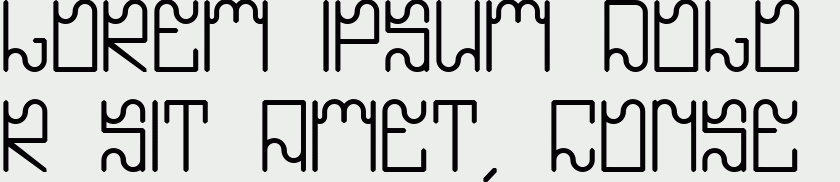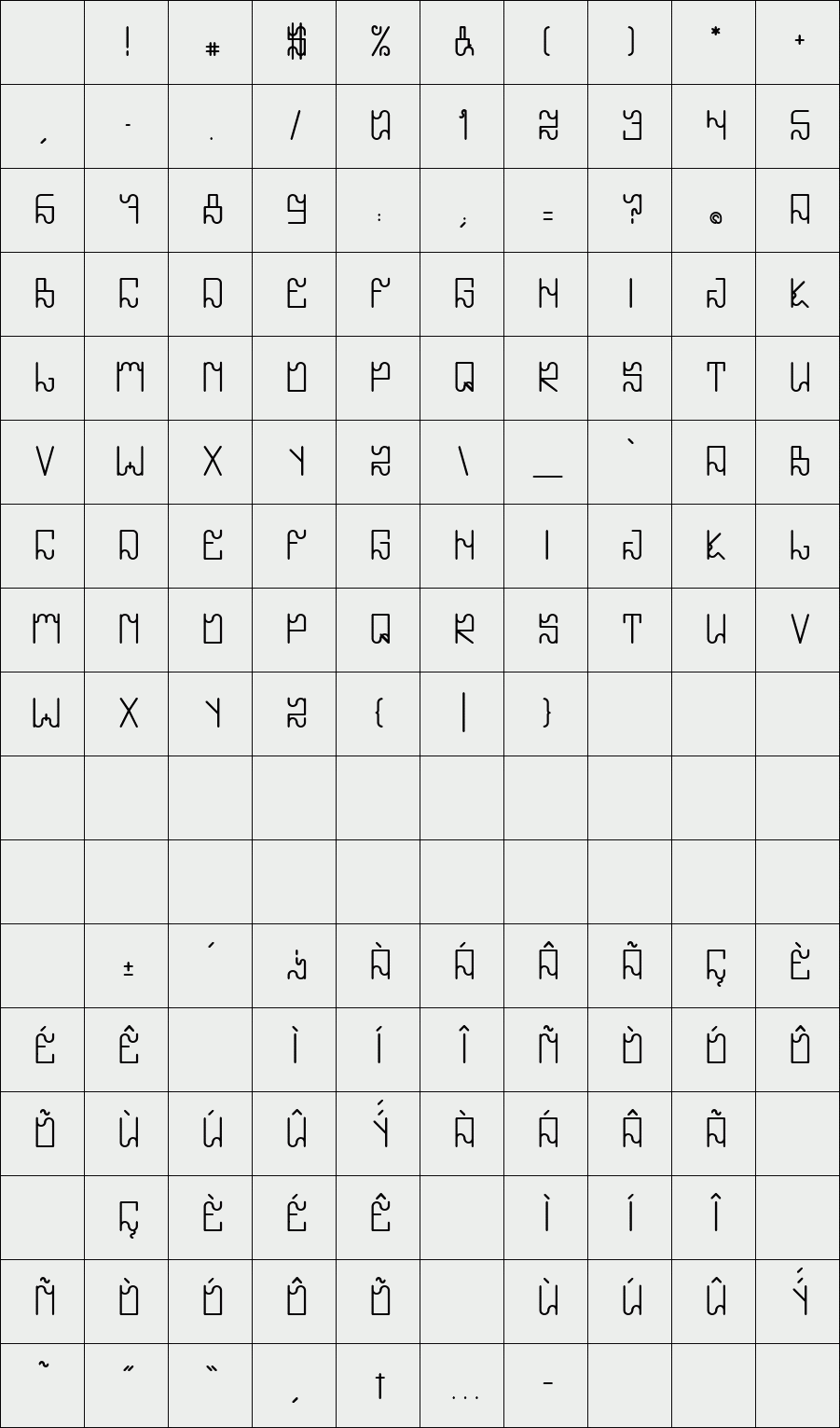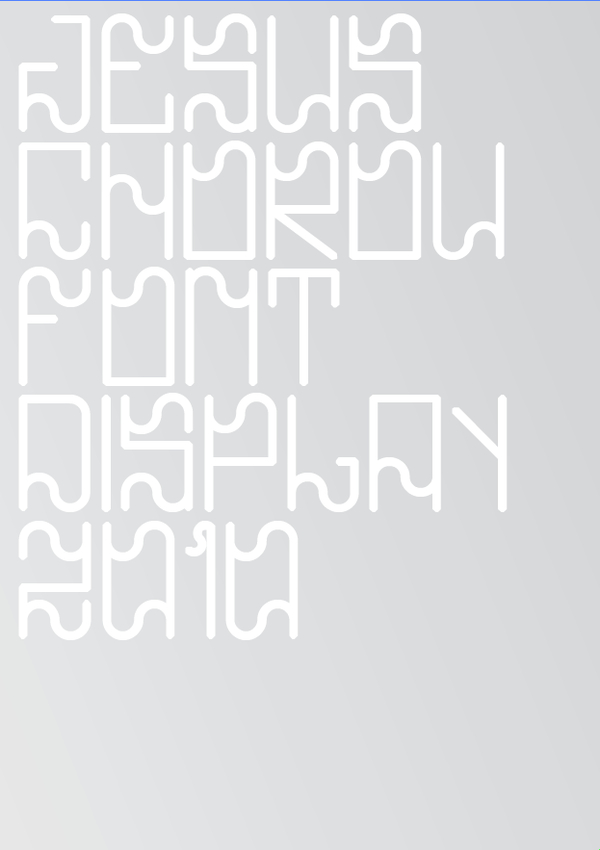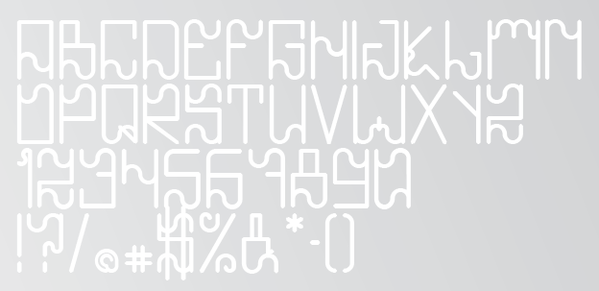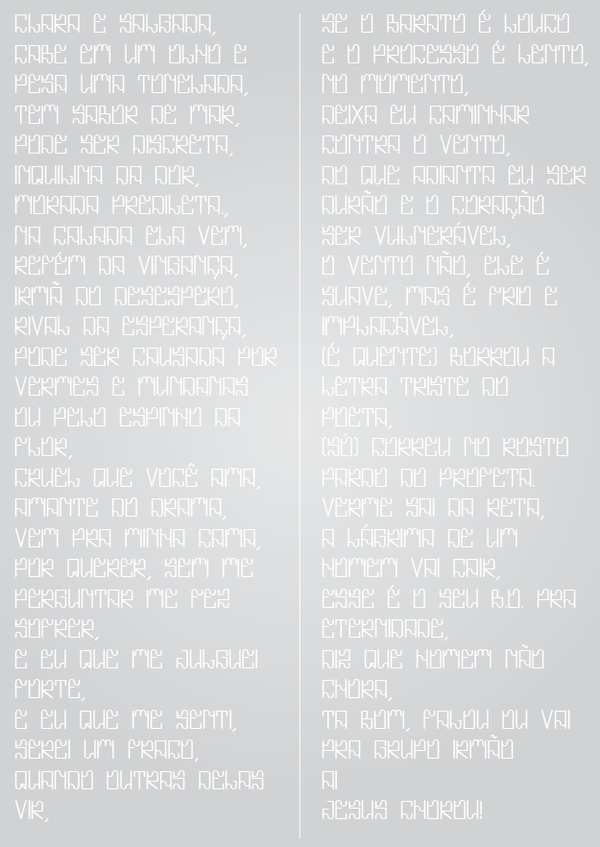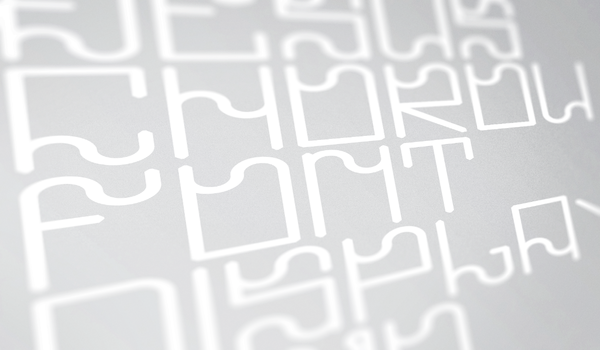
Jesus Chorou
Jesus chorou não é uma fonte porque sou ou não pixador e decidi fazer uma. É apenas um desenho que o skate, as companhias e os rôles de épocas passadas me inspiraram a fazer de uma forma descontraída e natural.
O nome foi inspirado numa música do grupo de Rap Racionais MC's.
Designer: Du Beluco